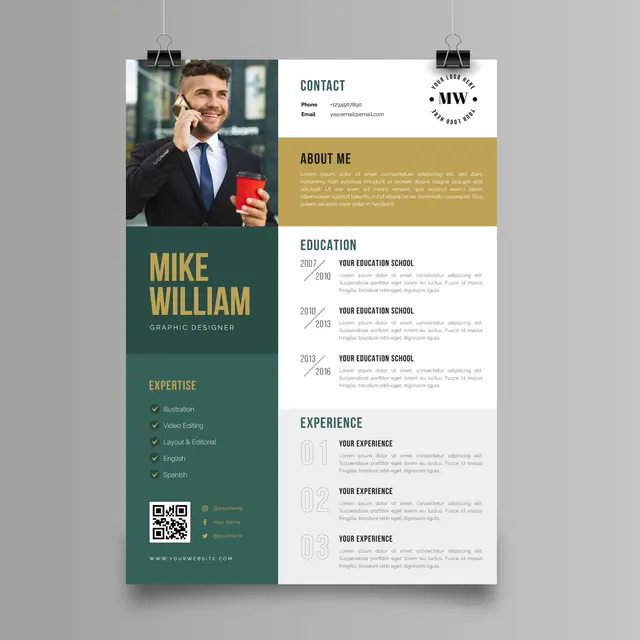
Liputan6.com, Jakarta Ada beberapa tips yang perlu dipertimbangkan saat ingin menulis resume kerja. Jadi, jangan sampai menulis resume yang asal-asalan jika ingin lolos ke tahap selanjutnya dalam melamar pekerjaan.
Selain memastikan menggunakan bahasa yang baik dan benar, gunakanlah kata kerja untuk merangkai kalimat dalam mendeskripsikan pekerjaan yang sesuai dengan pengalaman.
Di samping itu, dalam menggambarkan apa yang Anda lakukan di setiap pekerjaan, ada baiknya jika menghitung pencapaian tersebut dengan angka yang mengesankan.
Itu semua cukup mudah dilakukan. Akan tetapi, ketika Anda mencoba ingin membuat kesan, haruskah Anda menambahkan warna ke resume kerja agar lebih menonjol?
Misalnya, resume yang standar ditulis dengan font hitam, haruskah Anda mempertimbangkan untuk menggunakan warna seperti hijau atau ungu?
Tergantung perusahaan dilamar
Ketika berbicara tentang font warna-warni, para ahli setuju bahwa itu sangat tergantung pada industri tempat Anda melamar.
“Jika Anda seorang akuntan atau orang IT, tidak ada yang benar-benar menginginkan akuntan yang kreatif,” kata pendiri dan kepala strategi karir di The Bauke Group Julie Bauke.
Itu mungkin berlaku untuk industri lain juga, seperti keuangan dan obat-obatan. Lebih baik gunakan Arial, Times New Roman atau Calibri, font hitam 11 poin pada resume putih atau berwarna krem.
Namun, ketika Anda berada di bidang yang bergerak di bidang kreatif, kata Bauke, seperti desain grafis atau animasi, “Anda punya lebih banyak ruang untuk bereksperimen,” ujarnya.
Akan tetapi, pelatih karier Octavia Goredema mengingatkan, “Penting untuk mempertimbangkan keterbacaan, dan warna-warna cerah bisa sulit dibaca.”
Jika Anda telah memilih warna selain hitam, coba cetak terlebih dahulu resume tersebut untuk melihat apakah bisa terbaca atau tidak sebelum mengirimnya.
Warna tidak akan membuat perbedaan dalam keterampilan
Jika Anda menambahkan sedikit warna, ingatlah untuk menjaga agar resume tetap bersih dan tetap menggunakan format tradisional.
“Jika Anda memiliki kotak di sini dan warna yang berbeda di sini dan panah mengarah ke sini, dan Anda mencoba untuk terlihat lucu, maka saya bingung,” kata Bauke.
Anda ingin memastikan bahwa itu mudah, bahwa orang dapat memahami apa yang telah Anda lakukan dan apa yang Anda cari.
“Jika Anda ragu tentang desain yang Anda pilih, mintalah seseorang yang lebih senior dari Anda dalam industri Anda, idealnya seseorang yang membuat keputusan perekrutan, untuk meninjau format resume Anda," jelas dia.
Yang terpenting, “Font biru atau hitam tidak akan membuat perbedaan jika keterampilan dan keahlian serta prestasi Anda tidak relevan dengan peran yang Anda lamar,” kata Goredema.
Jadi, pastikan Anda menyertakan pengalaman yang relevan dan poin-poin penting yang membuktikan bahwa perusahaan ini harus mempertimbangkan untuk mempekerjakan Anda terlepas dari font ungu, garis bawah berlekuk, atau elemen desain unik lainnya.